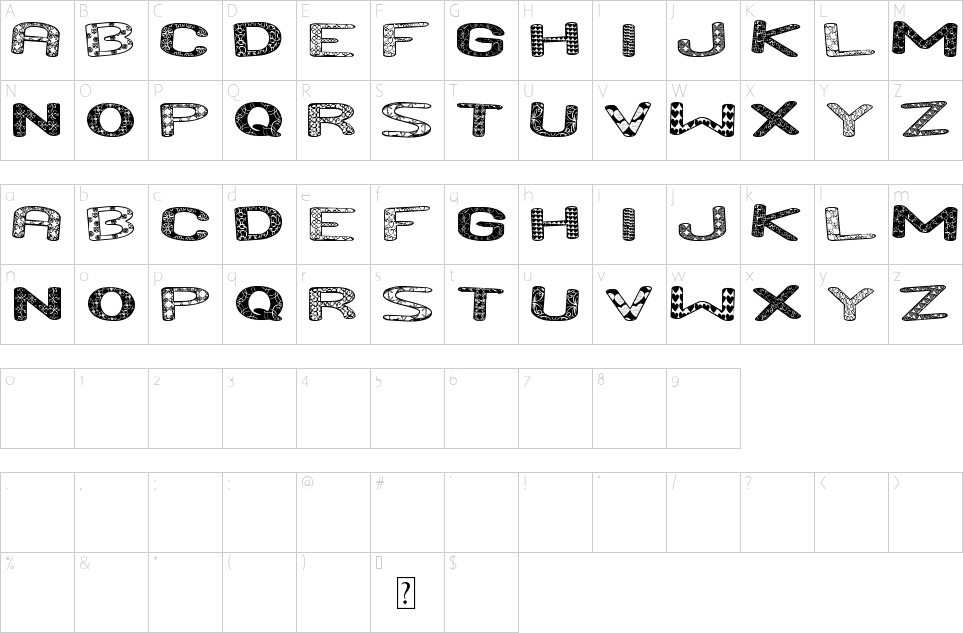
And Run Font – Download Grátis
A fonte And Run é uma opção gratuita que oferece uma aparência agradável para os designers e criativos. Desenvolvida pelo Southype, esta fonte é compatível tanto com sistemas Windows quanto com Mac. Seu design limpo e elegante permite que você personalize o texto de forma atraente em seus projetos. Com mais de 6.227 downloads, And Run é uma fonte popular para designers que buscam uma opção gratuita, prática e de alta qualidade. Seja você um criador de sites, designer de gráficos ou editor de fotos, And Run pode adicionar um toque especial a seus projetos digitais.